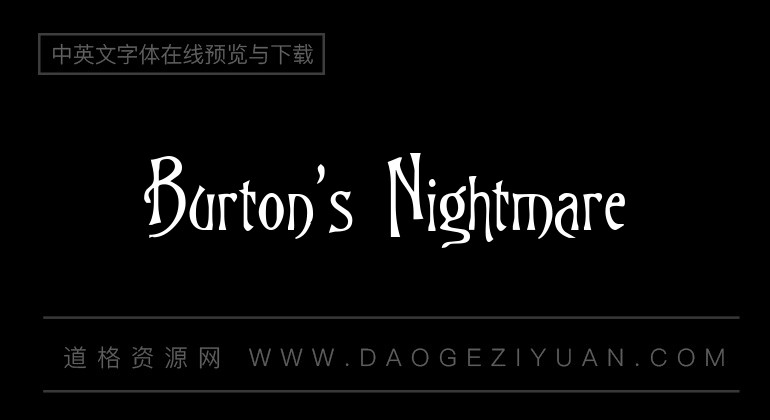
Burton's Nightmare 是一种由漫画家 Tim Burton 的笔迹所灵感创作的手写字体。它的设计灵感源自 Burton 的许多电影和艺术作品,包括《爱德华·剪手》、《夜魔侠》和《圣诞夜惊魂》等。 这种字体的特点是它的字母形状非常扭曲,像是在恶梦中被扭曲变形的字母。它的线条很粗,轮廓很突出,使得字母在页面上很显眼。这种字体一般被用在与 Tim Burton 相关的艺术和设计项目中,如海报、广告、书籍封面等。内容介绍
Burton's Nightmare是一款非常不错的手写艺术字体,具有很好的视觉感,适合于文化类的宣传设计、商业类品牌的广告和产品包装设计以及个性化文字排版等较多场景。